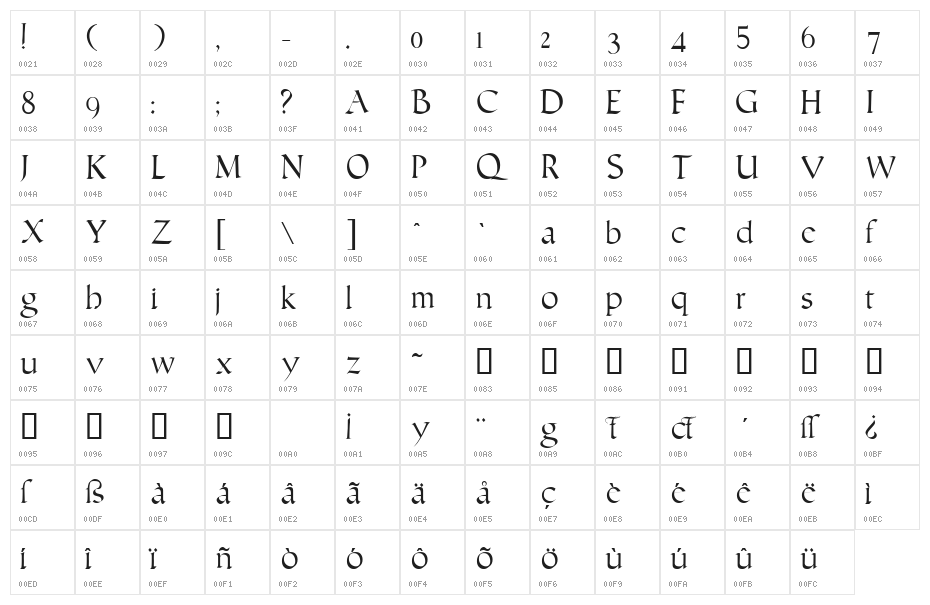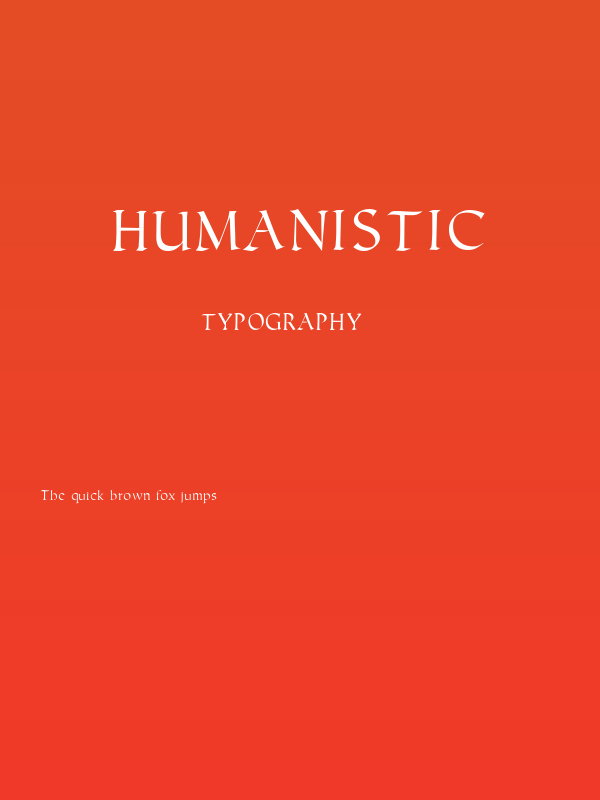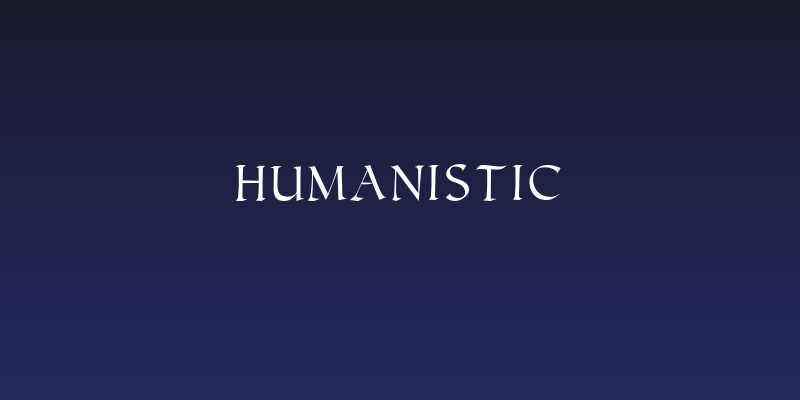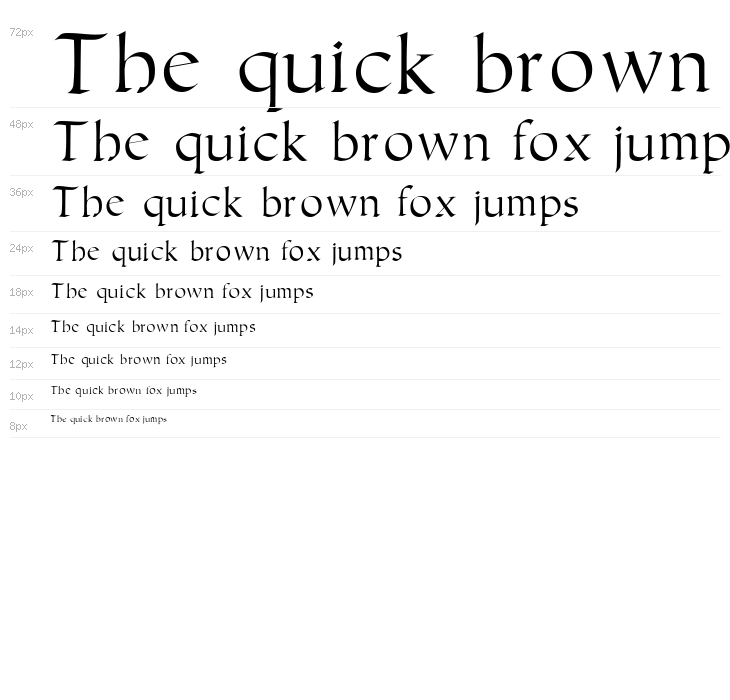
Humanistic Font
✎ Calligraphic
| श्रेणियाँ | Calligraphic |
| समग्र शैली | Classic |
| उपयोग का मामला | Headlines, Logos, Invitations |
| सुझाए गए प्रोजेक्ट | Ideal for projects requiring a touch of elegance and tradition, such as wedding invitations, formal event programs, or luxury brand logos. |